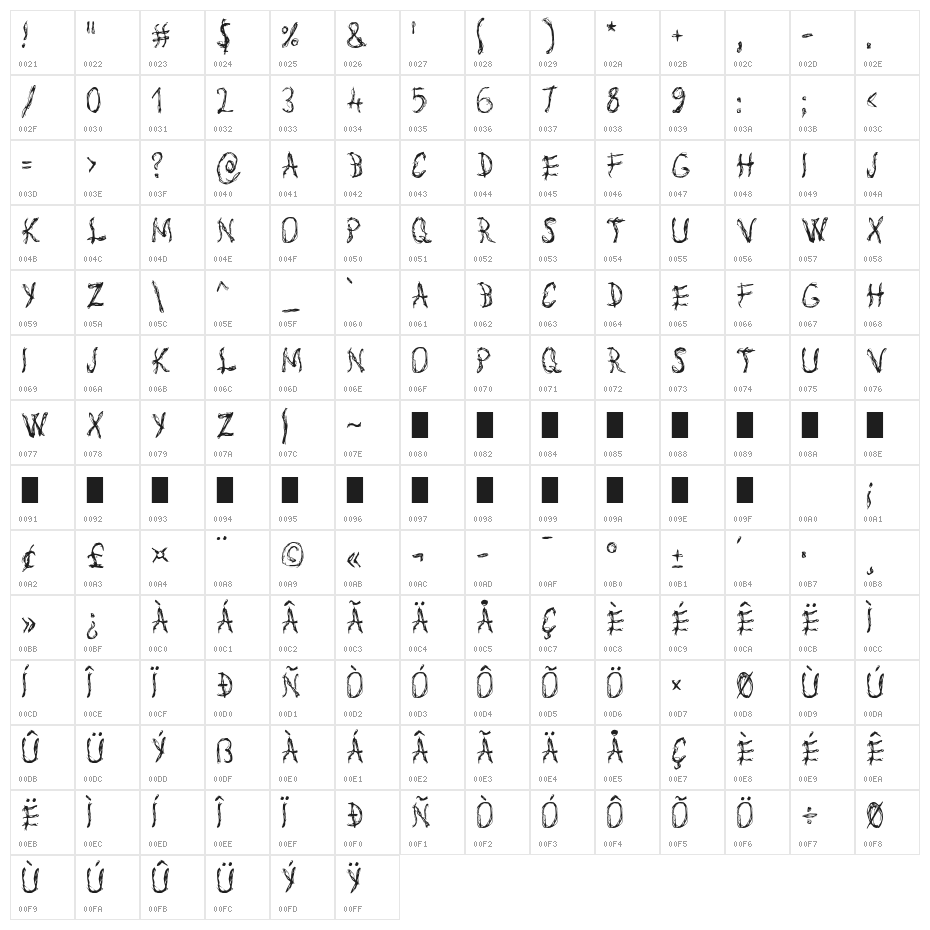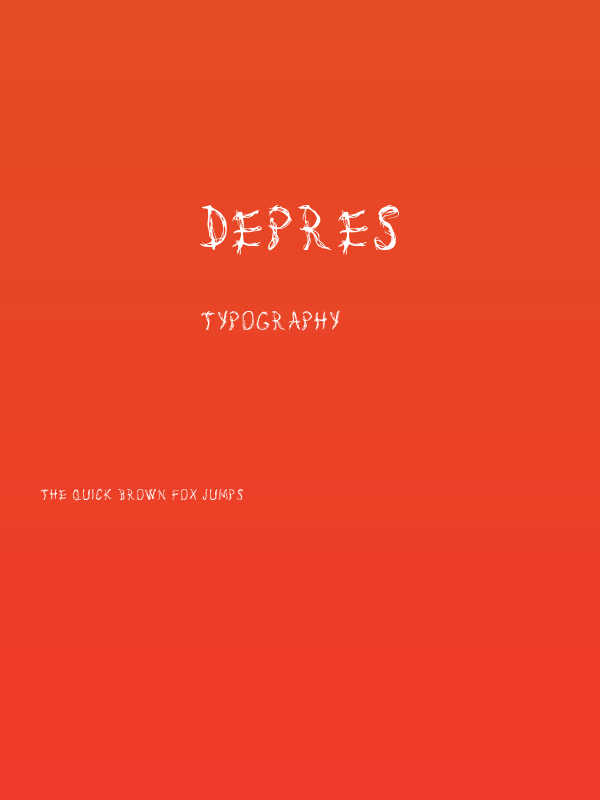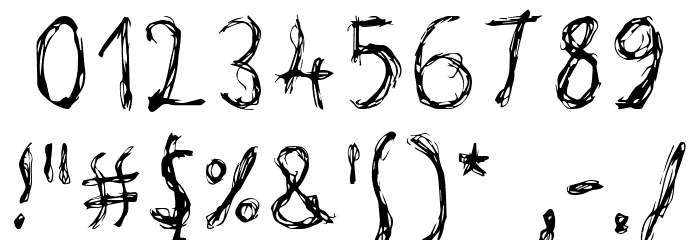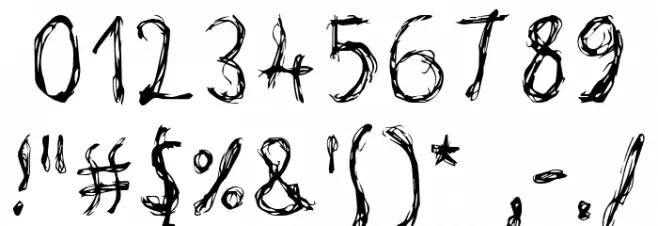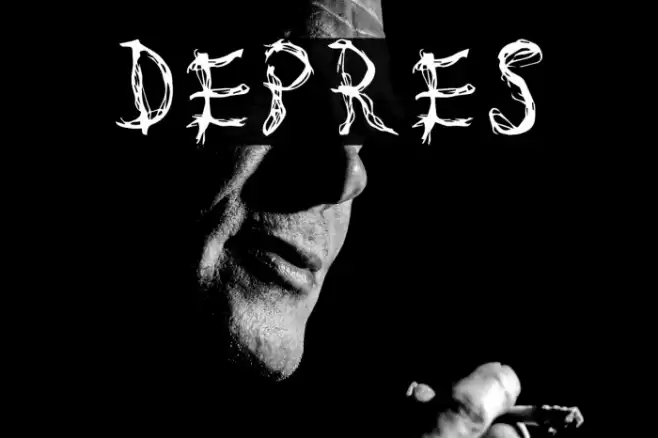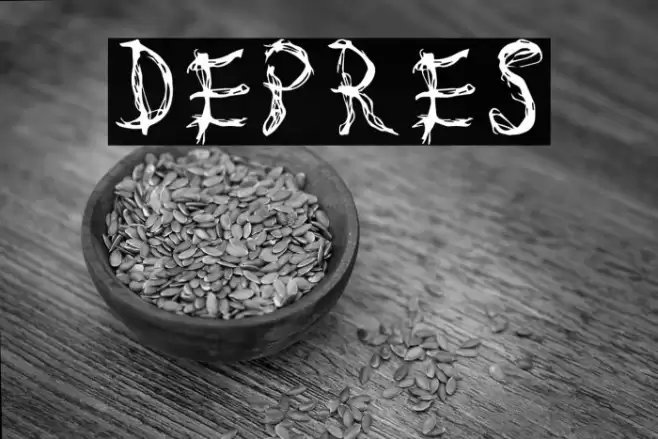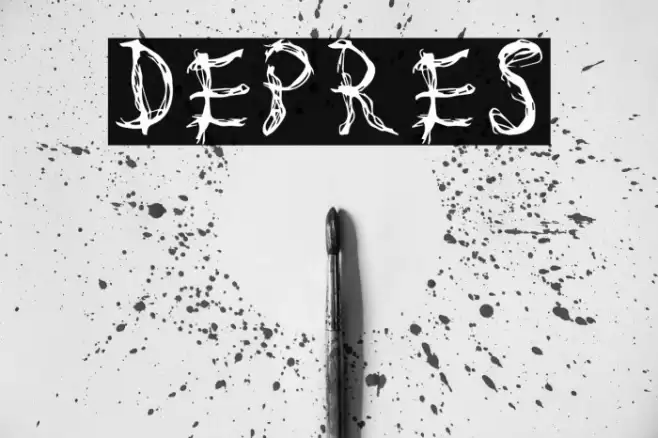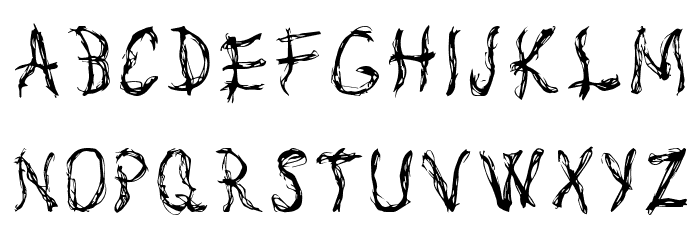
Depres Font
| 使用场景 | Logos, Posters, Artistic Designs |
| 推荐项目 | Ideal for horror-themed designs, album covers, posters, and artistic projects requiring a dramatic flair. |